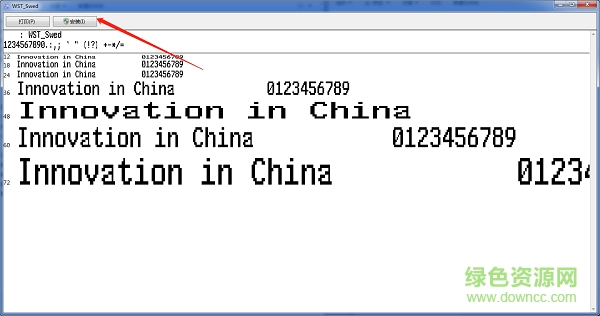
WST_Swed英文字體
WST_Swed字體簡(jiǎn)介:
WST_Swed英文字體是一款英文像素字體。它的特征非常的明顯,看起來(lái)像是用小方塊組成的字體,就跟我們?cè)趌ed廣告牌子上看到的英文字母的效果是一樣的,唯一有點(diǎn)遺憾的是這款字體目前不支持漢字內(nèi)容!